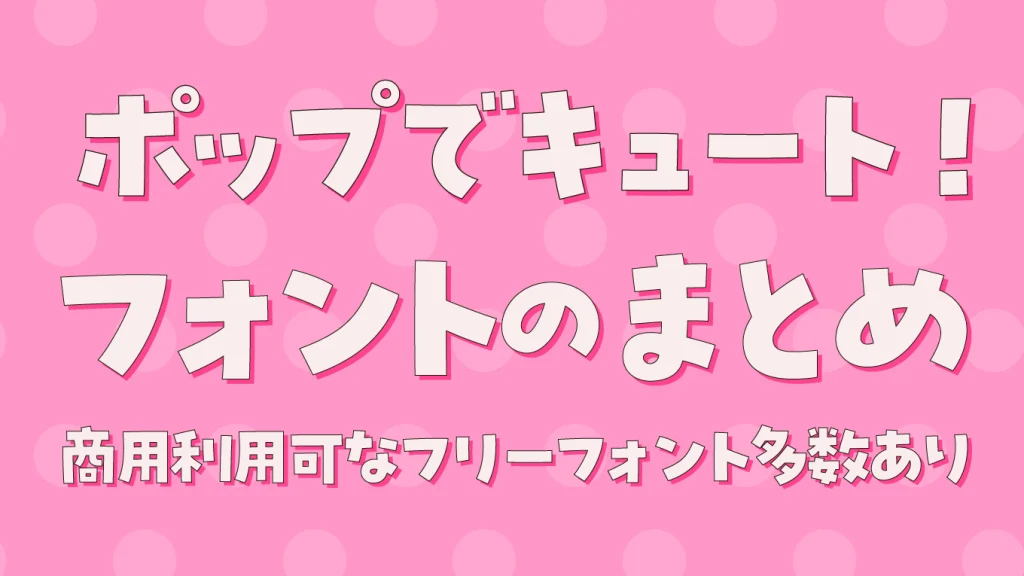
「ポップでキュート」な日本語フォント40選
今回は、「かわいい!」と声が出そうな、ポップでキュートな日本語フォントをご紹介します。 ころんとした丸み、リズミカルでちょっとハズした文字感、手描き風の温かみなど、そんな遊び心いっぱいのフォントは、デザインやグッズ制作、 hellip; 続きを読む 「ポップでキュート」な日本語フォント40選